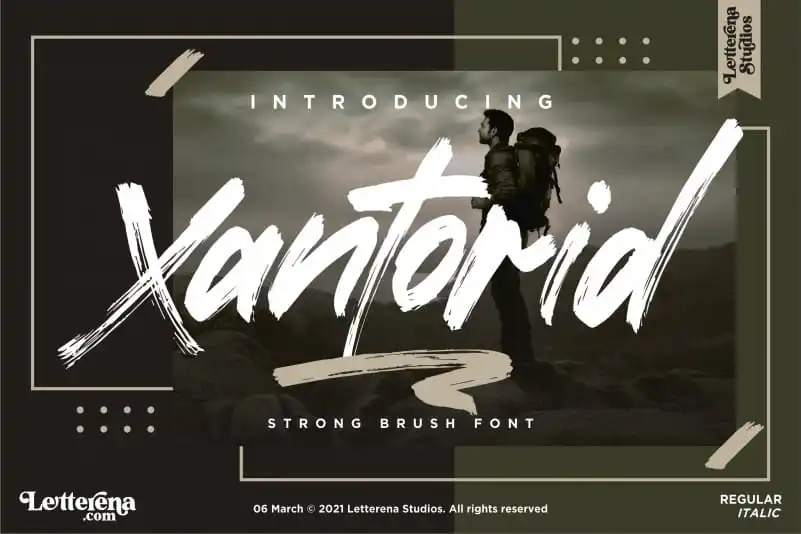
Xantorid Font – Fonte Grátis
Xantorid Font
A Xantorid Font é uma elegante opção para quem busca um touch suave e sofisticado na sua identidade visual. Desenvolvida pelo Designer Letterena Studios, esta fonte brush é perfeita para transformar qualquer projeto em um luxo aprimorado, seja criando logos para marcas inovadoras ou design de embalagens sofisticadas para produtos. Com uma versatilidade impressionante, ela pode ser usada para desenvolver designs exclusivos para mugs e pratos, criação de posters com frases memoráveis, produção de cartões de visita e convites personalizados, bem como para gravações em livros e capas de revistas. A Xantorid é uma fonte que oferece um toque refinado, adequada a todos os projetos exigentes que buscam expressar elegância através do design gráfico.